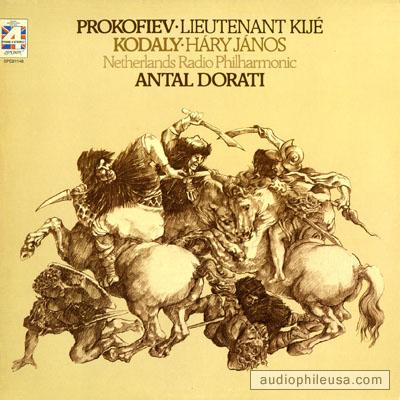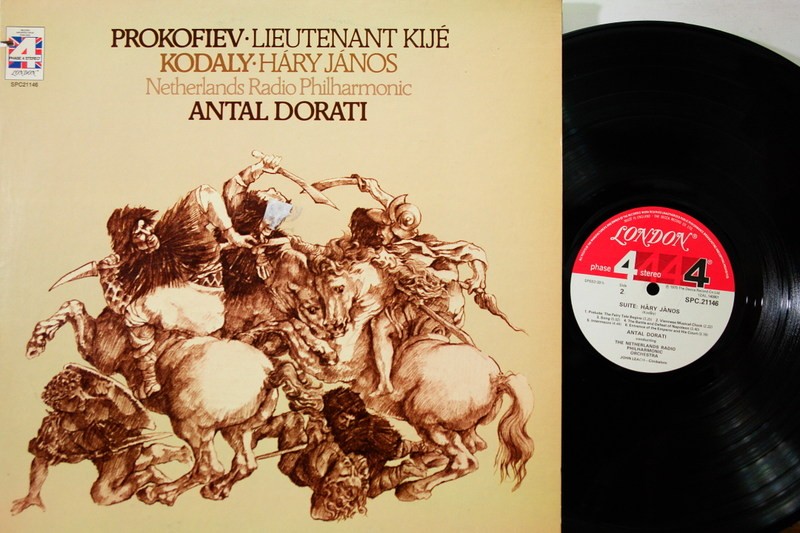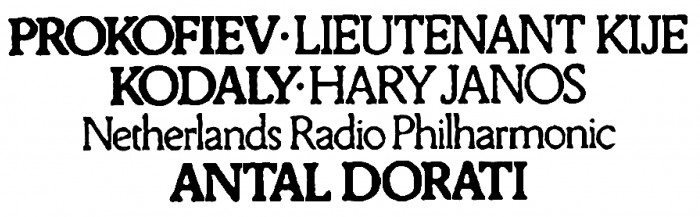
Suche (folgende) Schrift von Vinyl-Cover (1975)
Diese Schrift wurde von "DECCA/London" auf einem Schallplattencover verwendet. Ich habe schon verschiedene Suchen (What The Fonts, etc.) angestellt, habe aber keine "passenden" Fonts gefunden.
Signifikant scheint zu sein, dass die Strichstärke der Buchstaben prinzipiell "gleich" ist, dass die "runden" Buchstaben (O, D) fast kreisförmig sind und auch die Form des "kleinen e" ist "bemerkenswert.
Die Worte "PROKOFIEV, KODALY und ANTAL DORATI" sind (offensichtlich) "fett", der Rest ist "normal".